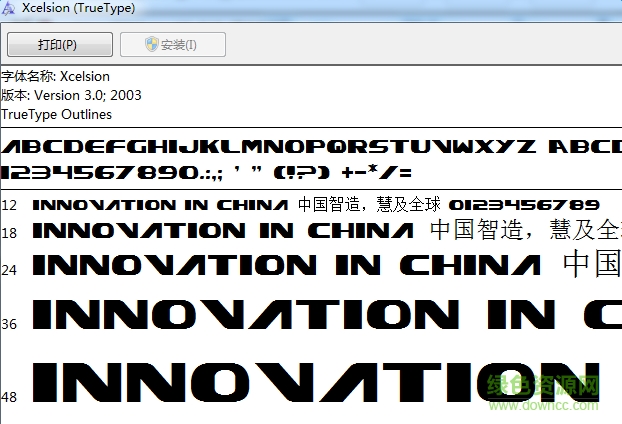
xcelsion字體是一款應(yīng)用個(gè)設(shè)計(jì)行業(yè)的英文個(gè)性字體,該字體可以廣泛應(yīng)用于廣告設(shè)計(jì)、宣傳海報(bào)、ppt、影視制作以及任何使用文字的領(lǐng)域,有需要的朋友可以免費(fèi)下載收藏。
xcelsion字體是一款英文字體庫(kù)中的個(gè)性字體嗎,該字體的形體較粗,顯得比較大氣,有需要的朋友可以來(lái)綠色資源網(wǎng)下載使用!